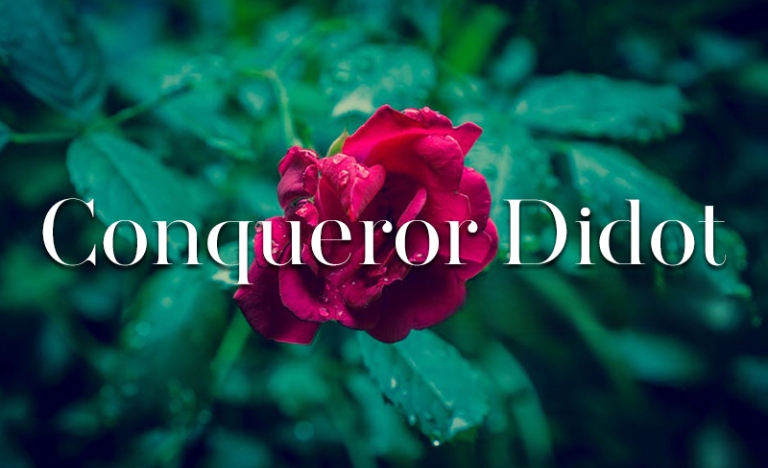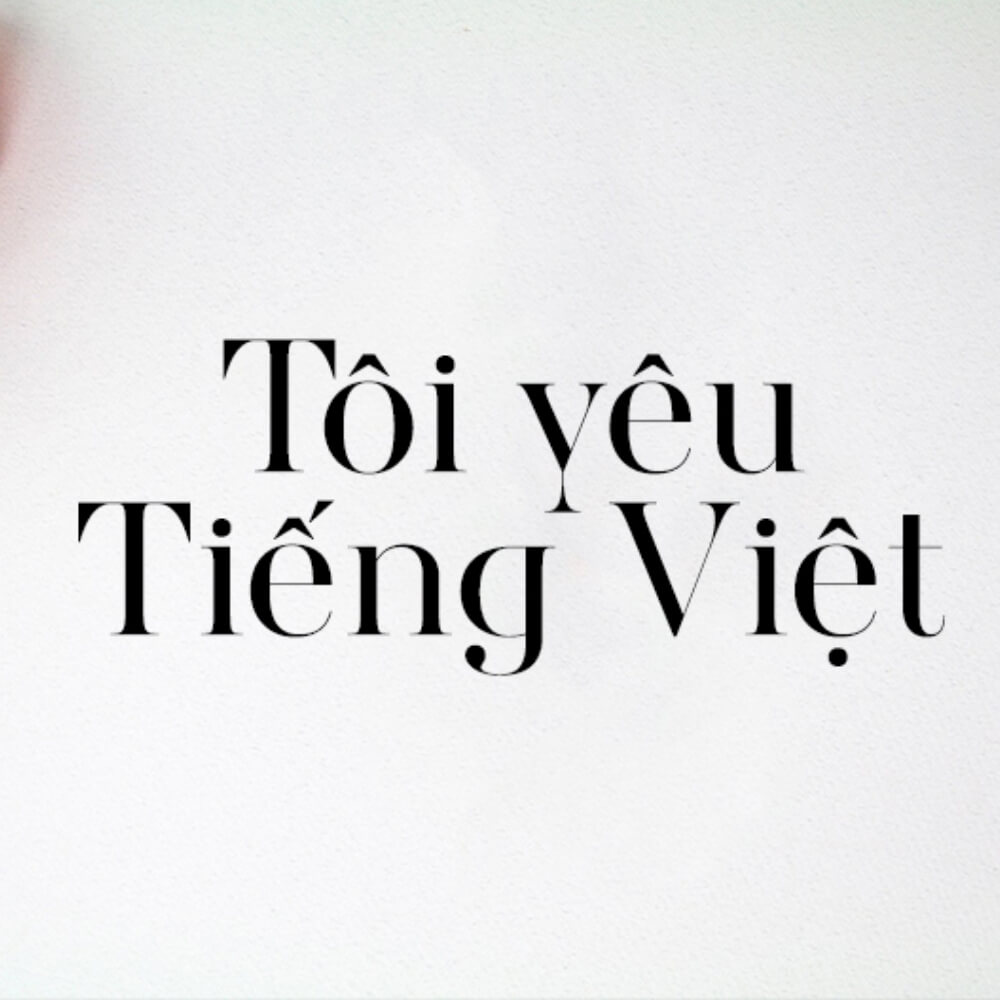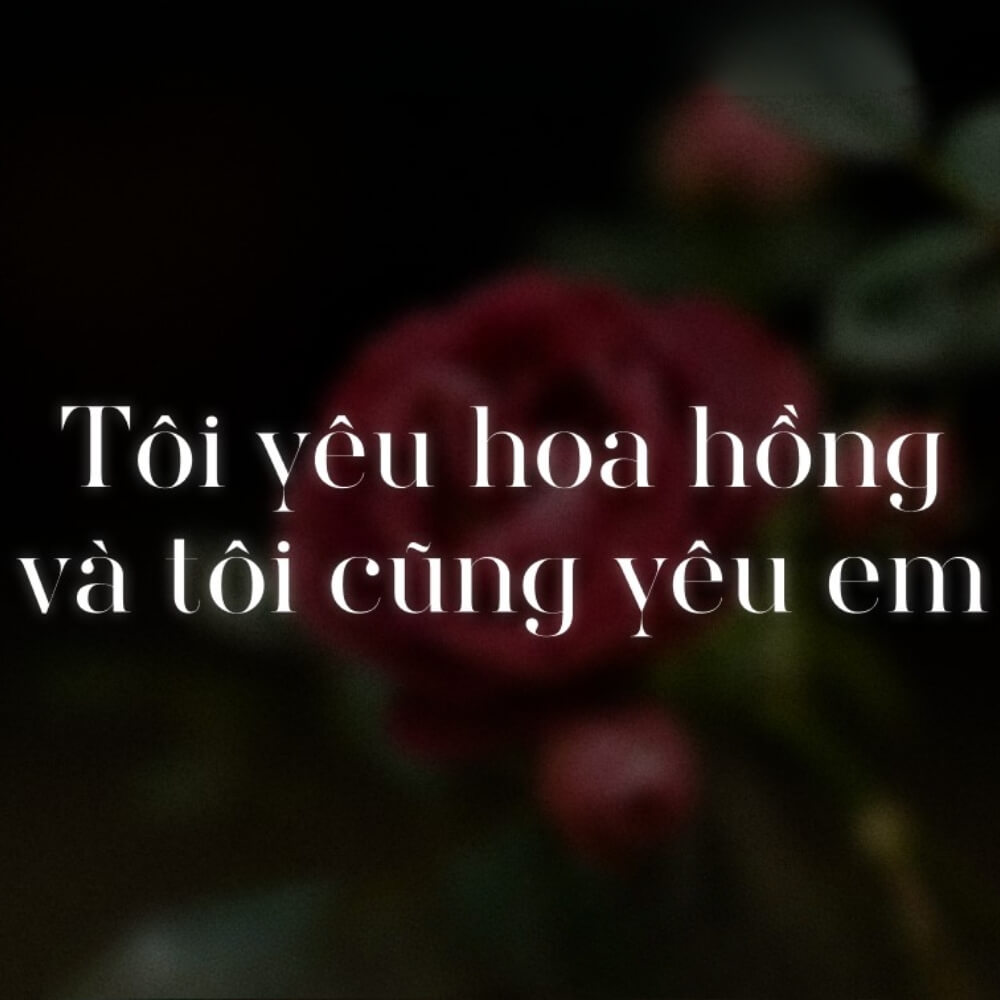
Didot là một trong những kiểu chữ kinh điển đại diện cho sự sang trọng, tinh tế và phong cách thời thượng nhờ sự tương phản mạnh mẽ giữa các nét thanh và nét đậm. Bộ font Việt hóa SVN Conqueror Didot mang đến giải pháp trình bày văn bản chuyên nghiệp cho người dùng tại Việt Nam, đặc biệt là trong các dự án đòi hỏi tính thẩm mỹ cao.
Đặc điểm thẩm mỹ của font chữ tiếng Việt SVN-Conqueror Didot
Điểm nhận diện rõ nét của svn didot chính là cấu trúc hình học chuẩn xác kết hợp với các đường nét thanh mảnh sắc sảo. Khác với các dòng font serif (có chân) truyền thống, SVN Conqueror Didot tạo cảm giác hiện đại và quý phái, gợi liên tưởng đến những ấn phẩm cao cấp trong lĩnh vực thời trang và kiến trúc. Bản Việt hóa đã xử lý kỹ lưỡng các ký tự có dấu, giúp duy trì sự cân đối và vẻ đẹp tinh tế của bộ chữ gốc mà không gây ra hiện tượng lỗi hiển thị văn bản tiếng Việt.
Sự tinh tế của bộ font này còn nằm ở khả năng tạo ra nhịp điệu thị giác rất tốt. Khi được trình bày trên các tiêu đề lớn, SVN Conqueror Didot thu hút ánh nhìn nhờ sự đối lập giữa những cột chữ vững chãi và các nét nối mượt mà. Đây là lựa chọn phù hợp cho các không gian cần thể hiện sự thanh lịch, chuyên nghiệp và có gu thẩm mỹ riêng biệt, giúp nâng tầm giá trị cho mọi sản phẩm thiết kế.
| Phân loại phong cách | Didone Serif / Modern Serif |
| Đặc tính nổi bật | Độ tương phản cao, chân chữ sắc nét |
| Mục đích phù hợp | Tiêu đề, Poster cao cấp, Logo, Branding |
Gợi ý phối hợp: Nhờ tính chất sang trọng của mình, bạn nên kết hợp font didot Việt hóa cùng một font không chân (Sans-serif) tối giản cho phần nội dung chi tiết. Sự tương phản giữa nét chữ thanh lịch của tiêu đề và sự gọn gàng của văn bản phụ sẽ tạo nên một bố cục chuyên nghiệp và dễ đọc.
03 Ứng dụng font Didot Việt hóa vào không gian sống
Với vẻ ngoài đậm chất nghệ thuật, bộ font chữ này mang lại giá trị thẩm mỹ ổn định khi được đưa vào thực tế trang trí và quảng bá các công trình mang phong cách hiện đại hoặc tân cổ điển:
- Bảng nhận diện cho Homestay & Boutique Hotel: Những nét chữ Didot rất ăn ý khi xuất hiện trên các biển hiệu bằng mica gương, inox hoặc khắc laser trên đá. Đối với các dự án nhà lắp ghép cao cấp, font chữ này giúp nâng cao vị thế và tạo ấn tượng mạnh với du khách.
- Thiết kế hồ sơ năng lực và Profile dự án: Sử dụng font này cho tiêu đề các hạng mục trong hồ sơ giúp thể hiện tư duy thẩm mỹ và sự chỉn chu của đơn vị tư vấn, giúp chủ đầu tư dễ dàng nhận diện tính chuyên nghiệp của dự án.
- Trang trí nội thất và Slogan tường: Bạn có thể dùng font chữ tiếng Việt svn-conqueror didot để làm decal trang trí hoặc uốn đèn led tại khu vực sảnh chờ, phòng họp văn phòng container nhằm tạo điểm nhấn đầy sang trọng cho không gian làm việc.
03 Lưu ý kỹ thuật để khai thác vẻ đẹp của SVN Didot trong thiết kế
Để duy trì được tính thẩm mỹ cao của dòng font Didot mà không làm ảnh hưởng đến khả năng tiếp nhận thông tin, người thiết kế nên lưu tâm một số điểm sau:
- Tránh sử dụng cho văn bản dài: Do độ tương phản giữa các nét quá lớn, Didot sẽ gây mỏi mắt nếu trình bày ở kích thước nhỏ và mật độ dày. Hãy dành font này cho các tiêu đề lớn hoặc các câu trích dẫn ngắn.
- Kiểm soát độ phân giải in ấn: Các nét thanh của Didot cực kỳ mỏng. Khi thực hiện in ấn bảng hiệu hoặc poster, bạn cần đảm bảo tệp thiết kế đạt độ phân giải cao để các nét mỏng không bị mất đi hoặc nhòe mờ.
- Lựa chọn màu sắc tương phản: Font Didot đạt hiệu quả thị giác cao khi đặt trên các nền màu đơn sắc như đen, trắng, vàng đồng hoặc các màu trung tính đậm để tôn vinh sự sắc sảo của từng chân chữ.